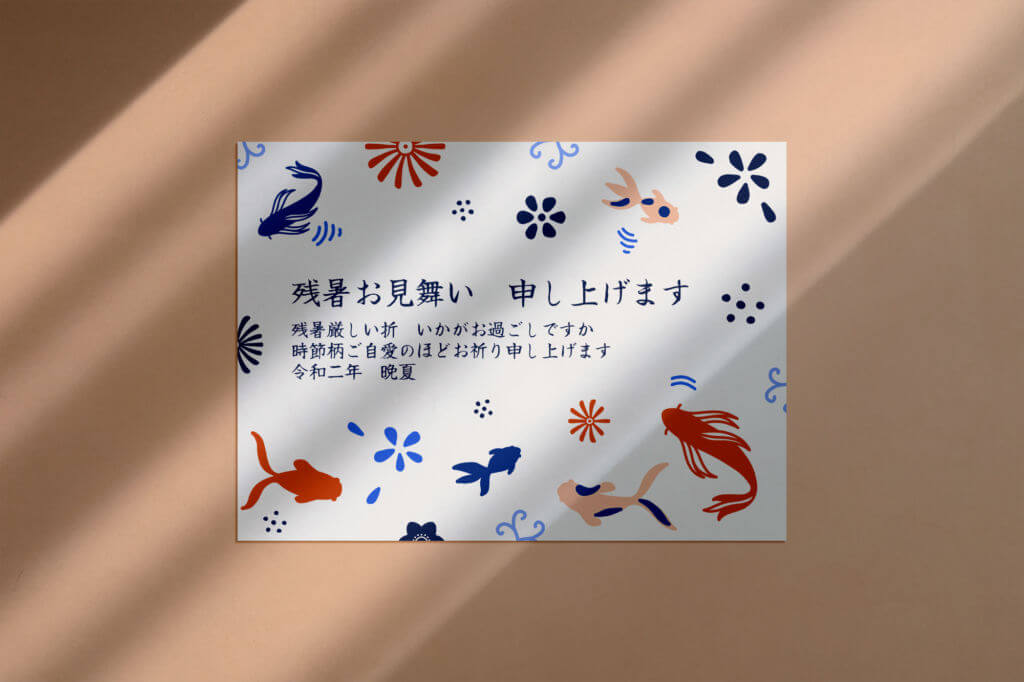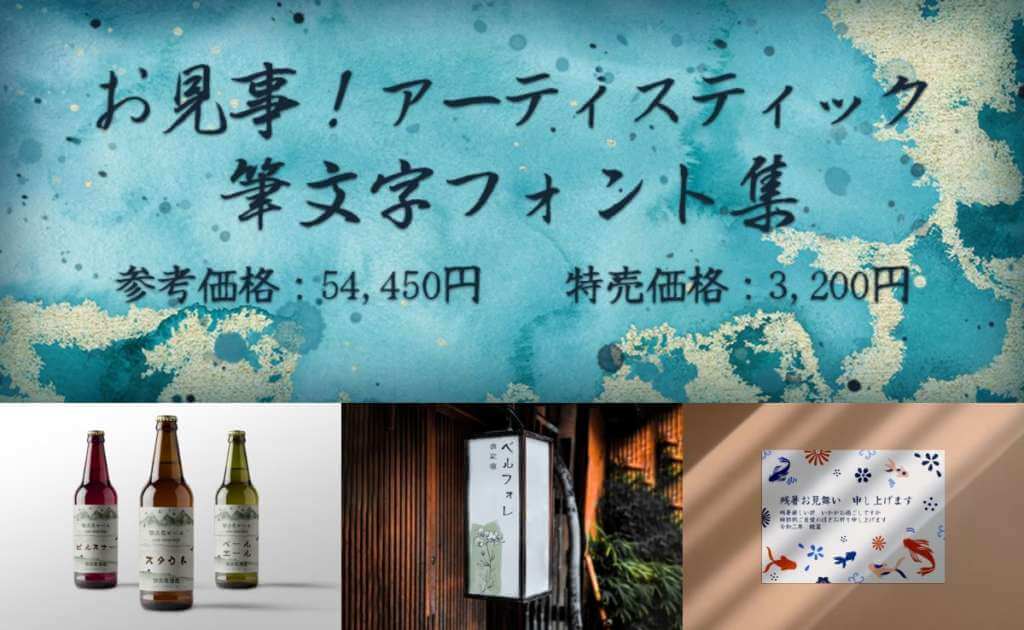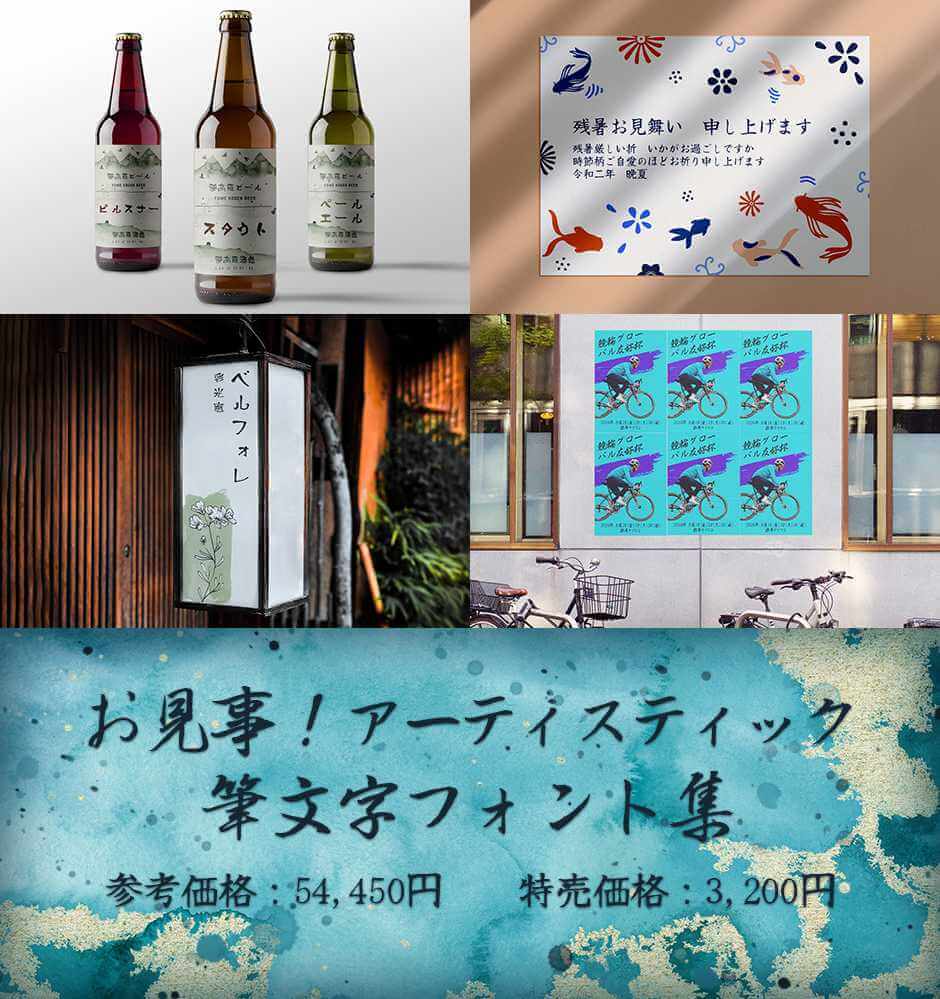
今回のバンドルは「お見事!アーティスティック筆文字フォント集」。ロゴやポスター、年賀状など幅広く使える個性的な日本語筆文字フォントが、お買い得な価格のコレクションになりました。
「お見事!アーティスティック筆文字フォント集」の気になる中身
宮城英生フォント集
文字アーティストとして活動する宮城英生氏による手書き毛筆フォント。個性的な3書体で和テイストなデザインの幅が広がります。
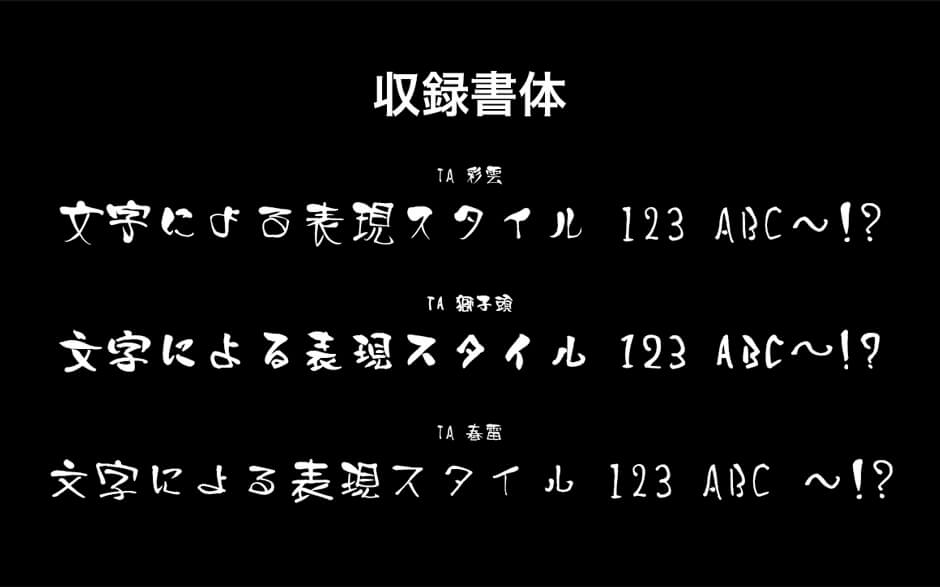
- TA彩雲
- TA獅子頭
- TA春雷
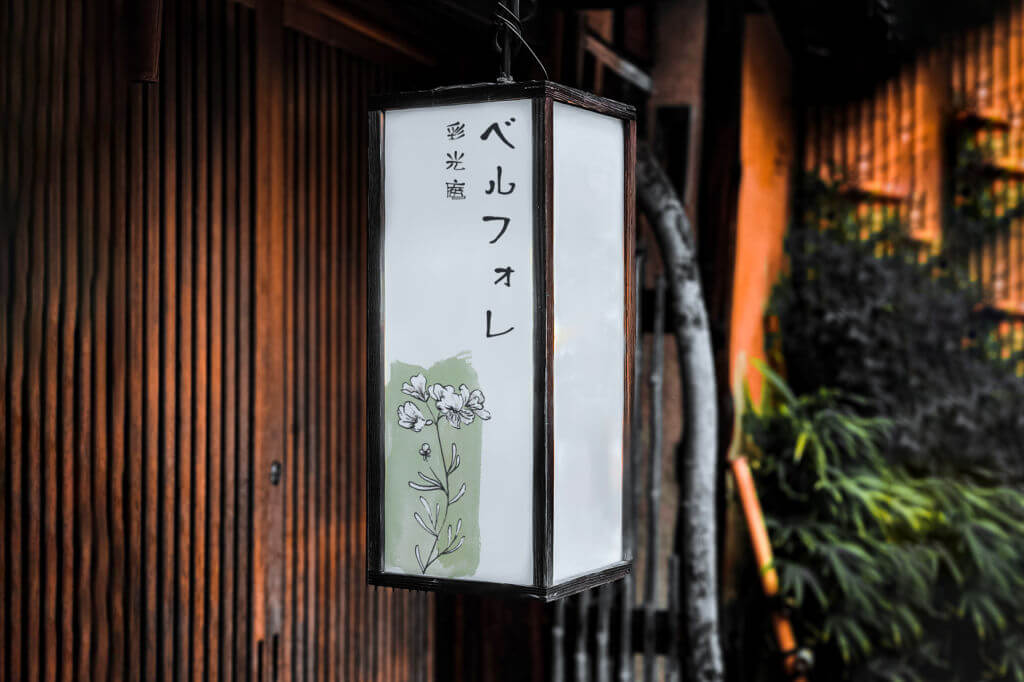
優美書体シリーズ
凛とした雰囲気が漂う「優美」シリーズから、デザインカッツ厳選の3書体をセレクト。長文でも読みやすい楷書体や、ちょっとくずしたペン字風など、持っておくと便利なフォントが揃いました。
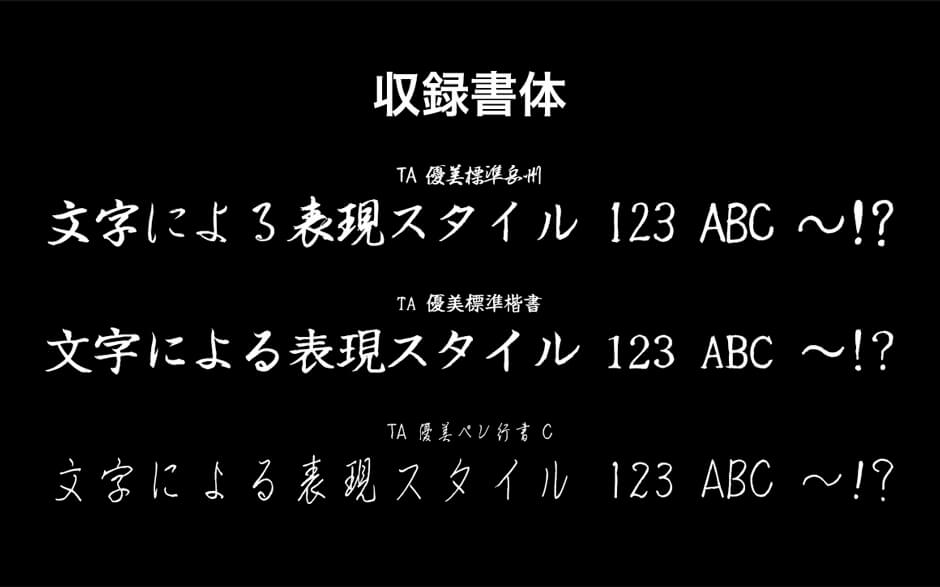
- TA優美標準岳州
- TA優美標準楷書
- TA優美ペン行書C